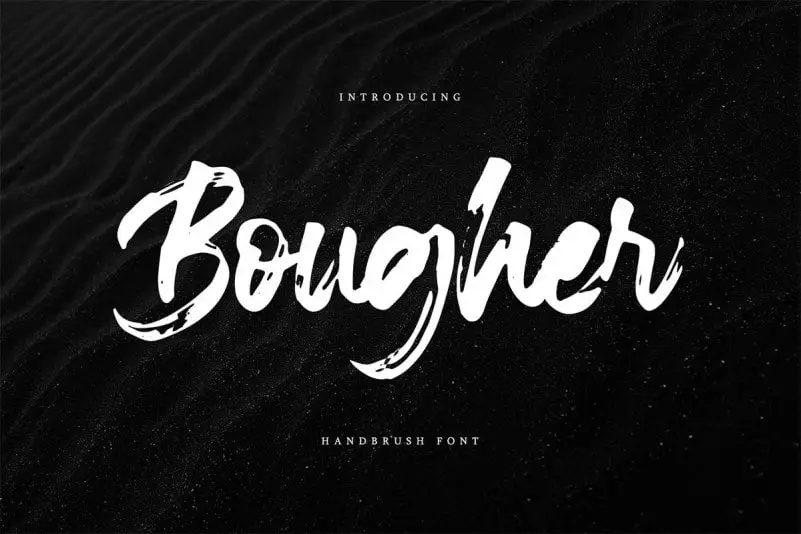
Bougher Brush Font – Download Grátis
Introduzimos a Bougher Brush Font – uma tipografia do tipo brush script criada pela Vztype com seus deslizamentos surpreendentemente impressionantes. Este tipo gráfico é perfeito para projetos de marca, logotipos, posts nas redes sociais, anúncios, embalagens de produtos, designs de produto, etiquetas e qualquer projeto que você esteja trabalhando. Com sua elegância e sofisticação, a Bougher Brush Font se destaca como uma opção excepcional para quem procura um tipo gráfico que transmite confiança e estilo com cada letra escrita. Seja no seu site pessoal, na sua marca ou em qualquer outro projeto de design, esta fonte trará um toque único à sua criação.